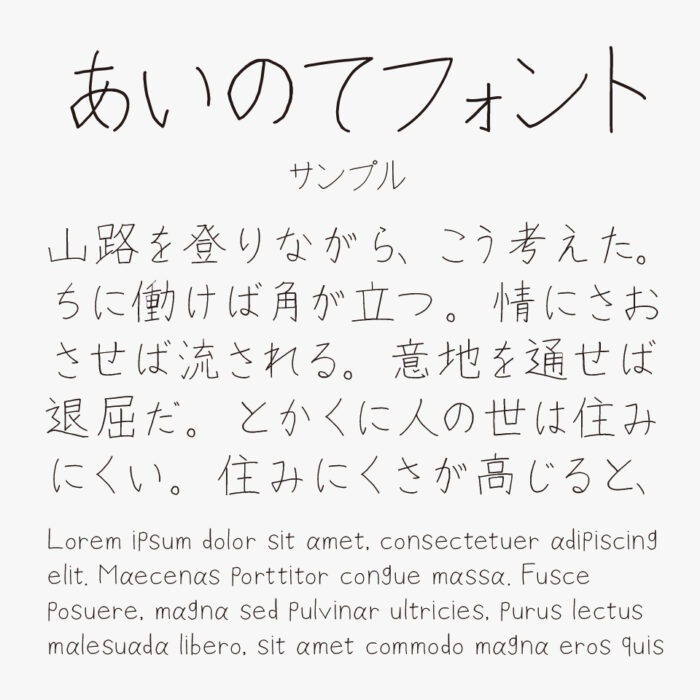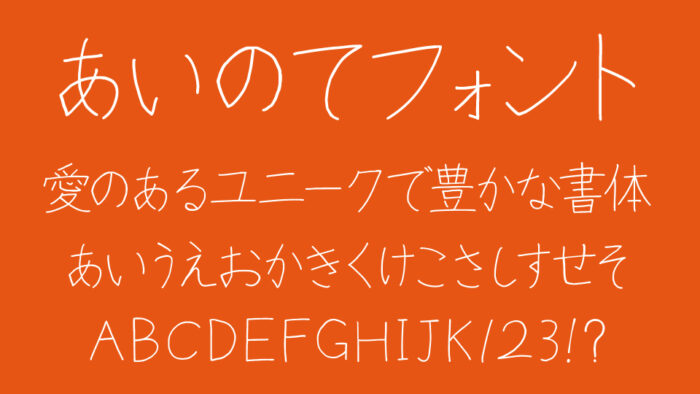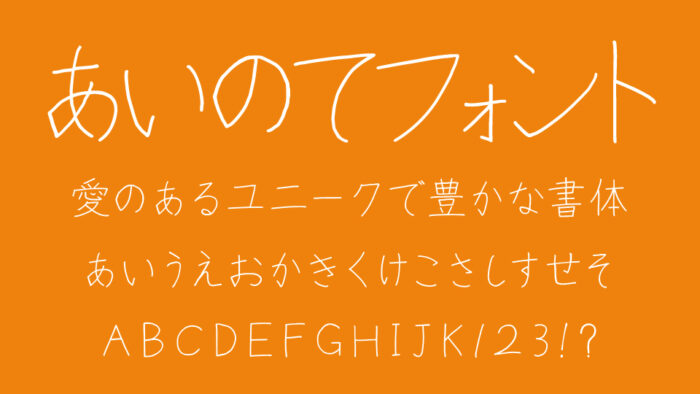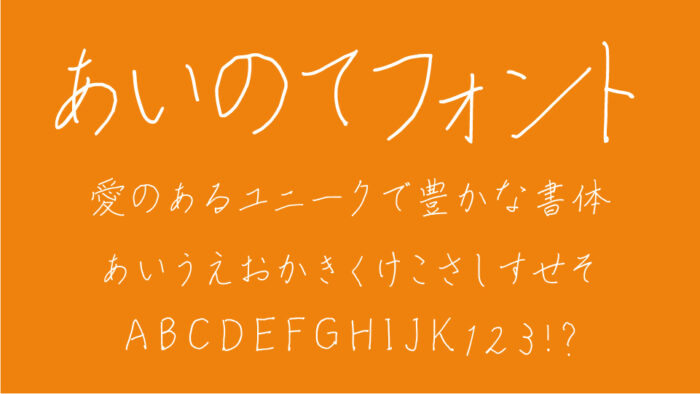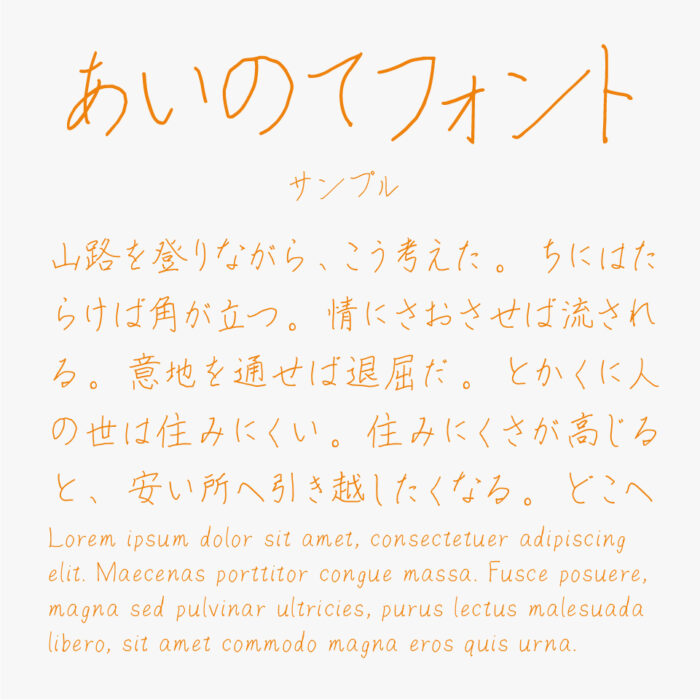
あいのてフォントは、相生創さんによる軽やかで風通しのよい手書きフォントです。
ボールペンのような細めで、柔らかな線と、ゆるやかなリズムが特徴で、感情を込めた「合いの手」のように文章に寄り添ってくれるような手書きフォントとなっています。細めのラインで余白を広めにとっているため、見た目に圧迫感がなく、親しみやすさを感じさせるデザインです。
| 漢字 | ○(教育漢字◯/JIS水準一部/漢検3級まで) |